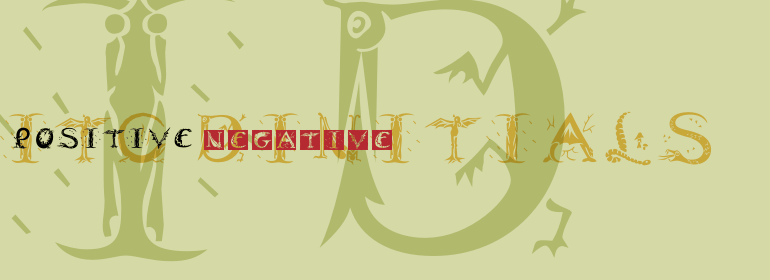
ITC Dinitials™
ITC Dinitials是德国设计师Helga Joergensen的作品。当我开始绘制第一个字母时,我受到了恐龙的极大启发,但是在工作中,我的想象力越来越驱使着我,后来就变成了一些很神奇的生物。“ITC Dinitials是个大写字母表,黑中有白,白中有黑。”
ITC Dinitials is the work of German designer Helga Joergensen. When I started drawing the first of them, I was very much inspired by dinosaurs, but during the work my fantasy guided me more and then became rather fabulous creatures." ITC Dinitials is a capital letter alphabet available in both black on white and white on black weights."